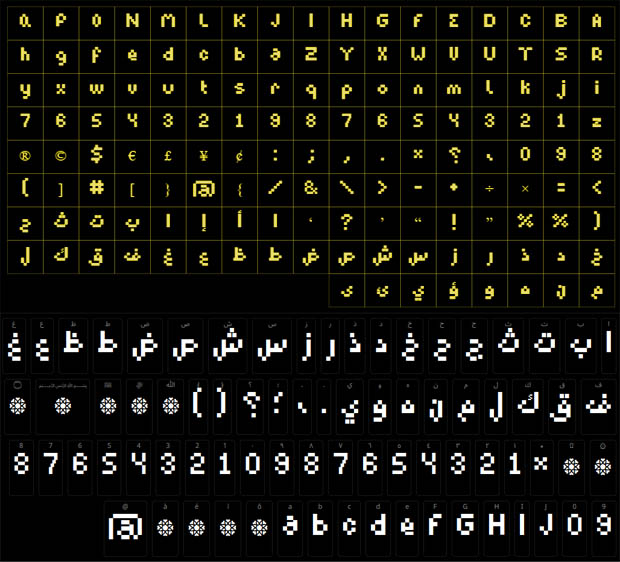
خط بيكسوبيديا للكتابة بالبكسل عربي وإنجليزي .. خط هندسي عربي وإنجليزي جميل، يكتب بالشكل البكسلي ويستخدم في الأعمال الفنية والألعاب والعناوين الملفتة للنظر، وهو متاح للتحميل المجاني الآن.